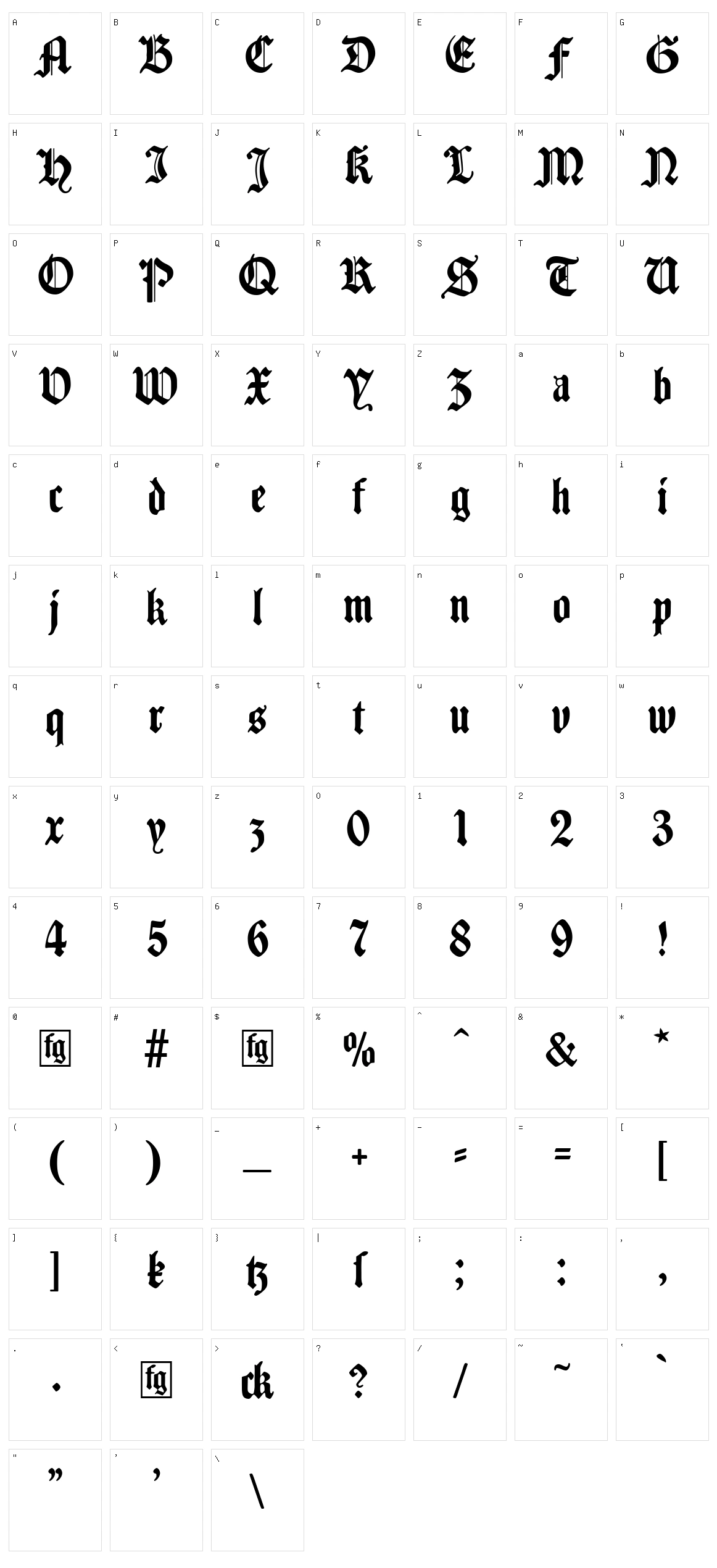
Traditio AH
Die Idee zur "Traditio" stammt von einem Schriftzug aus der Werbung. Die offensichtlich handgeschriebene Vorlage basiert auf Textur-Formen des 19. Jahrhunderts, hat aber sehr weiche Kanten.
Die wenigen Buchstaben der Vorlage habe ich zu einem vollständigen Alphabet ergänzt. Besonders die Versalien tragen oft Antiqua-ähnliche Züge, was für Ungeübte das Lesen erleichtert. Der lateinische Name "Traditio" ist der Vorlage entlehnt.
Based on German beer advertising, this typeface in the style of a 19th century Textura ("Old English") was elaborated in 2007-2013 by Andreas Höfeld (Fontgrube). Its uppercase characters are often close to the familiar forms of Latin Antiqua letters, which makes it more legible for modern readers. "Traditio" ist the Latin word for "Tradition", a word taken from the sample that inspired this font.